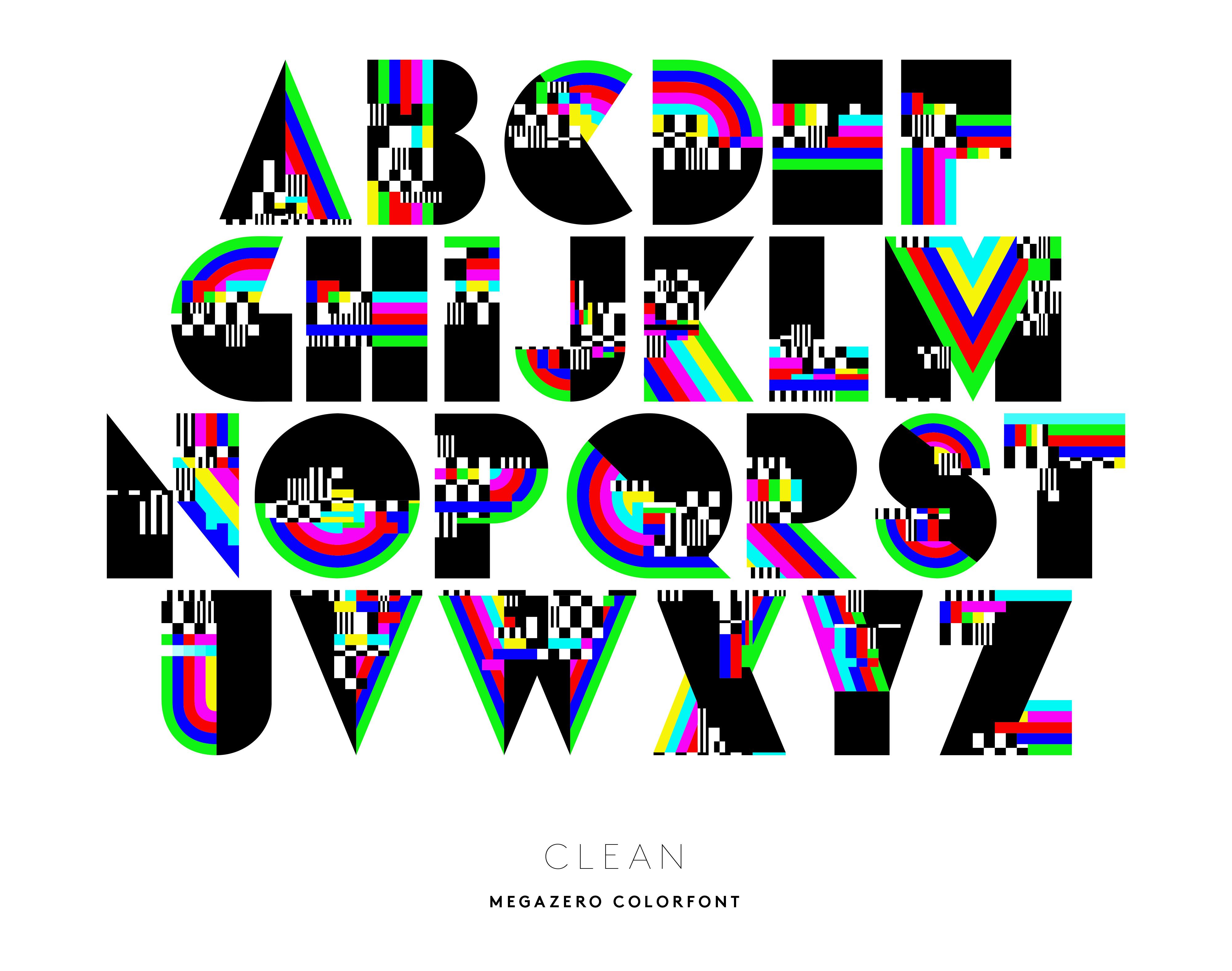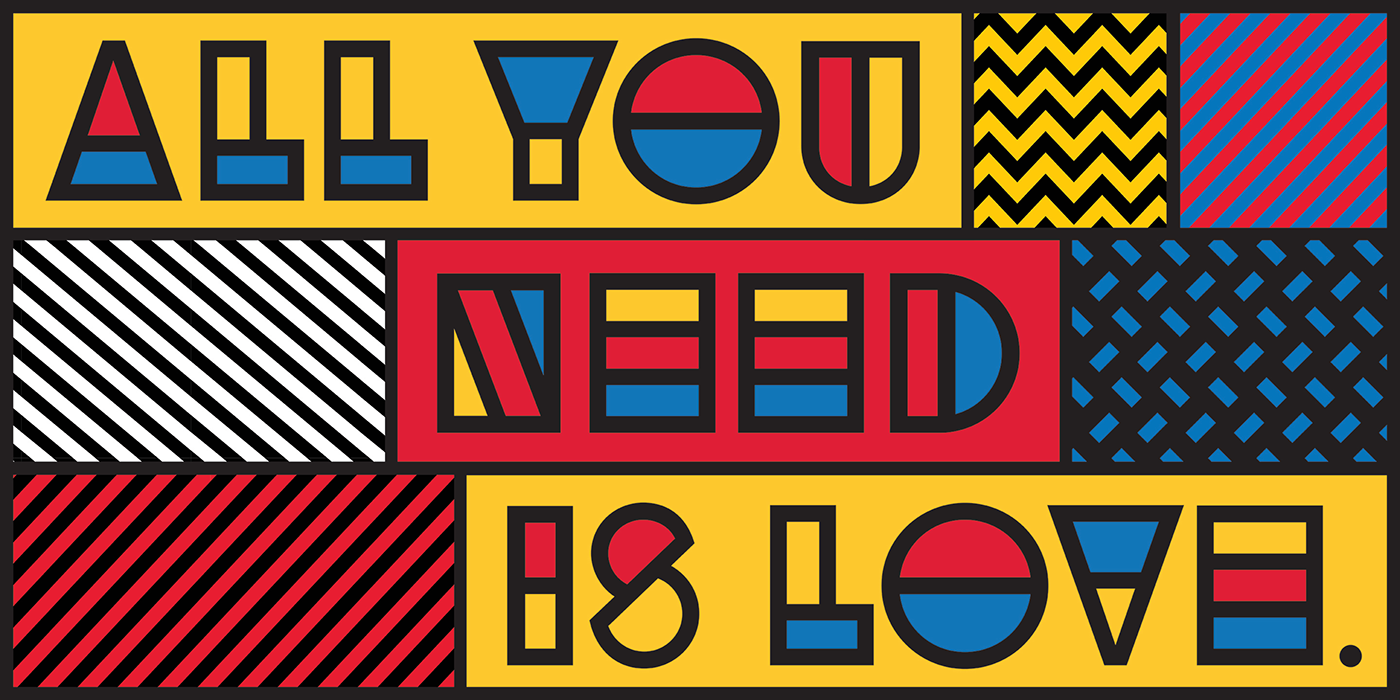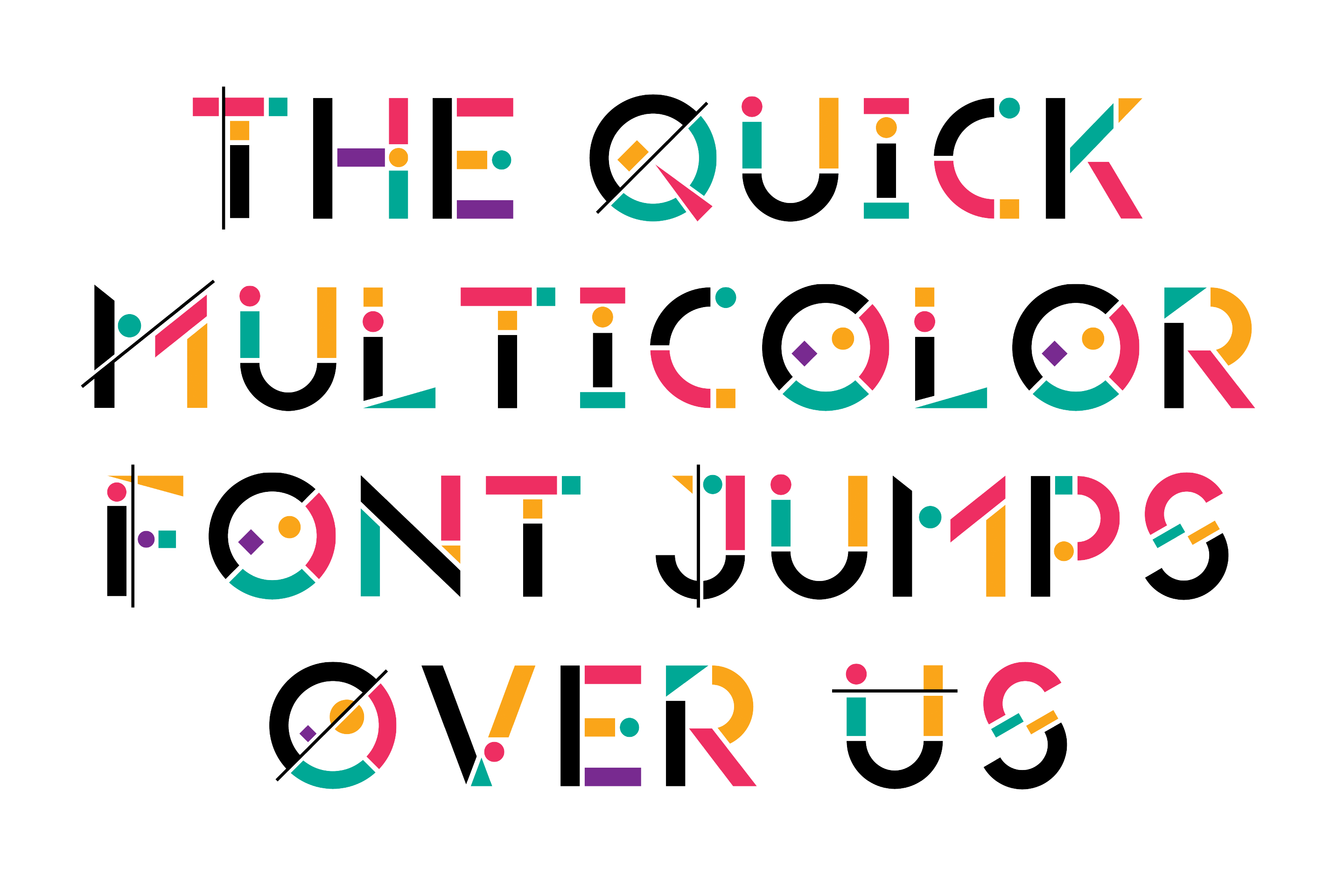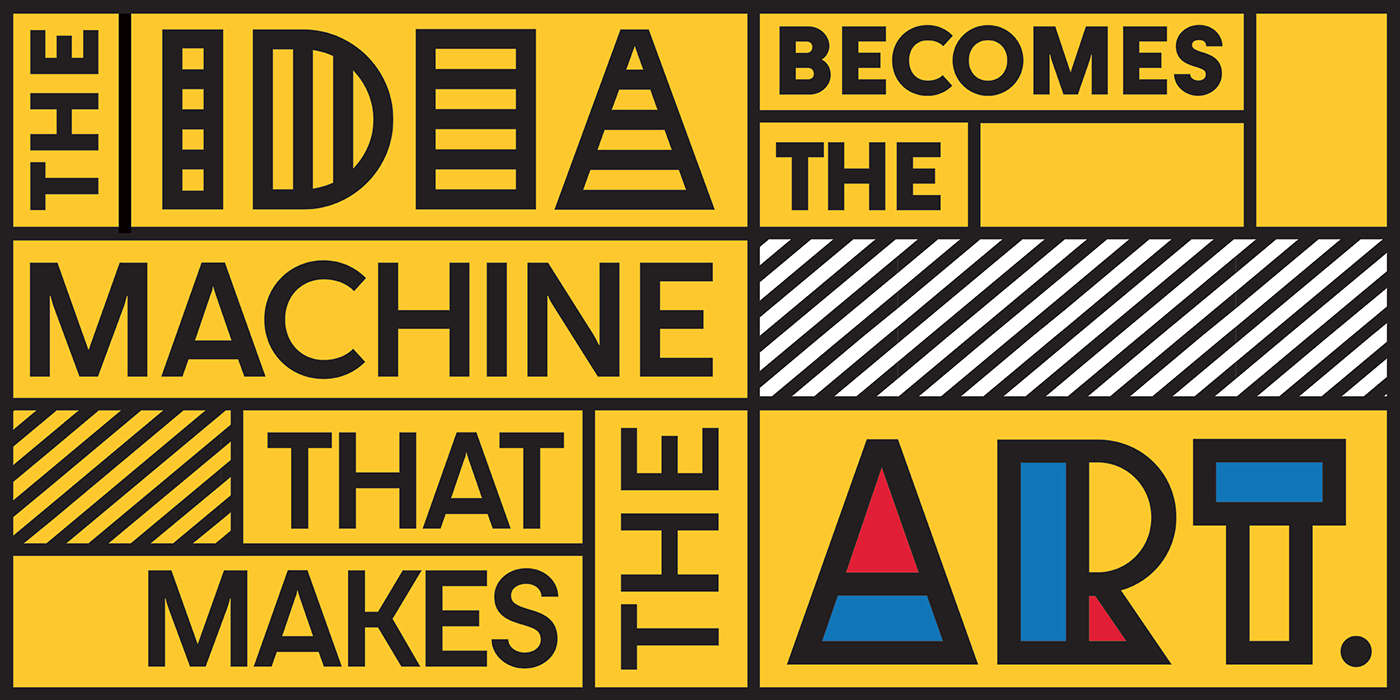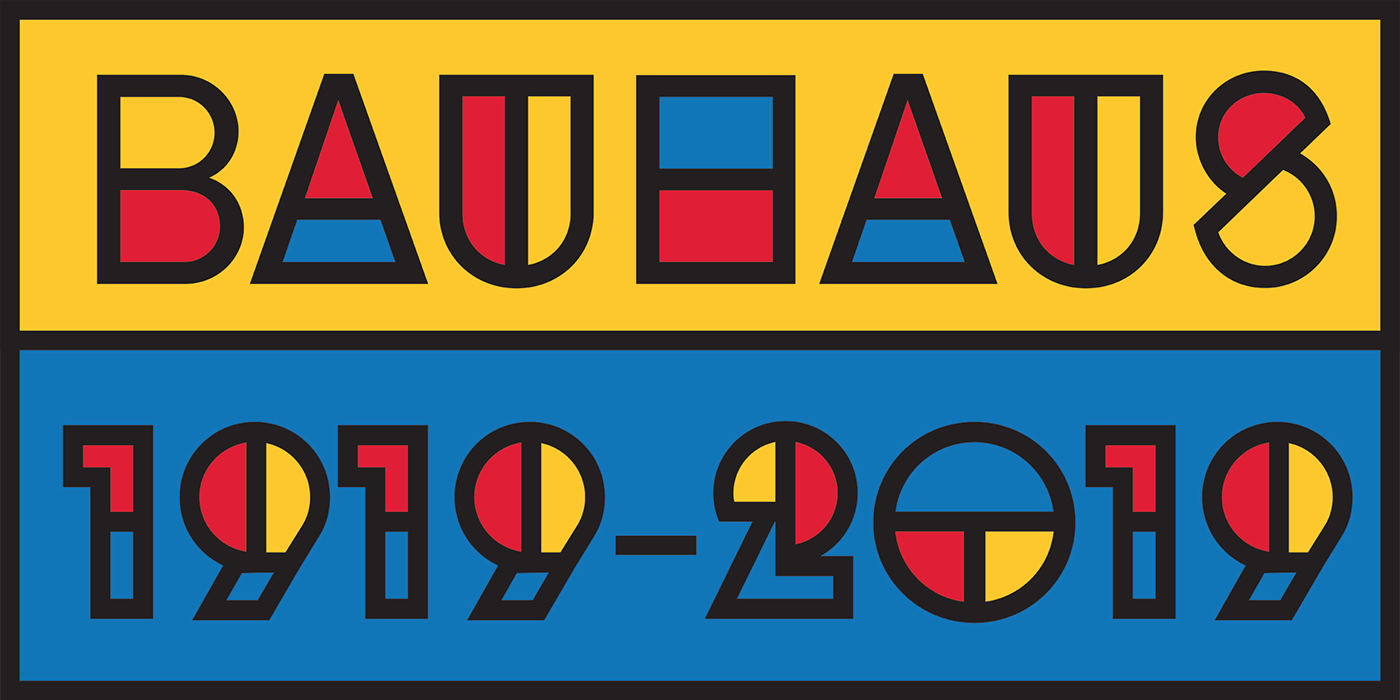
¿Qué es color font?
Hablamos con Alex Trochut acerca de una de las tendencias tipográficas más importantes actualmente: color font
Alex Trochut (@trochut), con su labor de diseñador gráfico, tipógrafo, ilustrador, lleva el lenguaje más allá de cualquier diseño de letras antes visto. A través del descubrimiento, la diversión y el asombro, Trochut descubrió que la palabra y el diseño no deben ser ilegibles, sino que deben transmitir la lectura del significado y lo visual, conjugarse de una forma diferente.
Por eso, no se nos ocurre nadie mejor que él, para que nos explique qué es color font, la nueva y colorida tendencia dentro de la tipografía y cómo puede generar un cambio en el diseño digital.
Color font diseñada por Alex Trochut y Sudtipos
¿Qué es color font?
Las color fonts son tipografías de texto "picable" a todo color. Son la próxima gran novedad en diseño gráfico. Cuentan con múltiples colores, matices, texturas y transparencias, incluyen formas vectoriales, imágenes de mapa de bits –o incluso ambos– en archivos de fuente.
Representan una evolución clave en la tipografía digital y pueden afectar a cualquier tipo de texto, ya que pueden contener todo tipo de caracteres, incluidos emojis e iconos.
¿En dónde se puede ver aplicada su función principal?
En cualquier contexto que permita el uso de tipografía display.
Color font diseñada por Alex Trochut
¿Cuál es el primer ejemplo de color font que se conoce?
La primera que surgió se llama Gilbert. Una tipografía gratuita hecha para honrar la memoria de Gilbert Baker (creador de la bandera arcoíris), una fuente gratuita inspirada en el lenguaje de diseño de la icónica Rainbow Flag. Fue diseñada para resaltar los titulares y declaraciones en pancartas dentro de mítines y protestas, pero se convirtió en una familia completa con pesos y estilos.
Además, se sumó la participación de Animography para darle movimiento a la tipografía, diseñado para animación, películas, vídeos, publicaciones sociales, GIFs y mucho más.
¿Cómo empezaste a realizar color font?
Empecé trabajando con Fontself Maker, un plugin para Illustrator y Photoshop que permite a los diseñadores convertir cualquier obra de arte vectorial en un tipo de letra, incluido el color, los degradados y cualquier otro tipo de diversión, abriendo un nuevo mundo de posibilidades. Resulta una herramienta muy fácil de manejar, puede ser un buen punto de partida para muchos diseñadores y para iniciarse en la tipografía.
¿Por qué crees que debería usarse más?
Añadir la dimensión del color en tipografía abre todo un nuevo abanico de posibilidades. El hecho de no depender solo del blanco y el negro para definir la forma y contraforma de la letra abre muchas posibilidades. Además, debido a la infrenable necesidad de generar contenido constantemente, el hecho de que una color font dote dé un aspecto visual más identificable y expresivo, se vuelve una herramienta muy provechosa para marcas y clientes que necesitan comunicar mensajes de forma rápida y reconocible.
Color font diseñada por Igor Petrovic
¿Qué formas puede adoptar esta nueva tendencia?
Cualquier vector o forma puede ser asignada a un caracter, siempre y cuando tenga menos de 1000 puntos. Las fuentes de color basadas en glifos vectoriales pueden redimensionarse sin ninguna pérdida, como cualquier fuente normal.
¿Dónde podemos encontrar color fonts?
¿Cuál es tu ejemplo favorito de color font?
La Utopian de Sudtipos está muy bien. Es una familia de fuentes de color basada en colores primarios y formas geométricas puras, influenciada por el Bauhaus, el DeStijl y el Art Deco. Sus formas puras y sus colores básicos están inspirados en la belleza de la simplicidad del orden modular y la cuadrícula, creando un ambiente perfecto donde todos estos elementos viven en una perfecta armonía de color.
Color Font Utopian